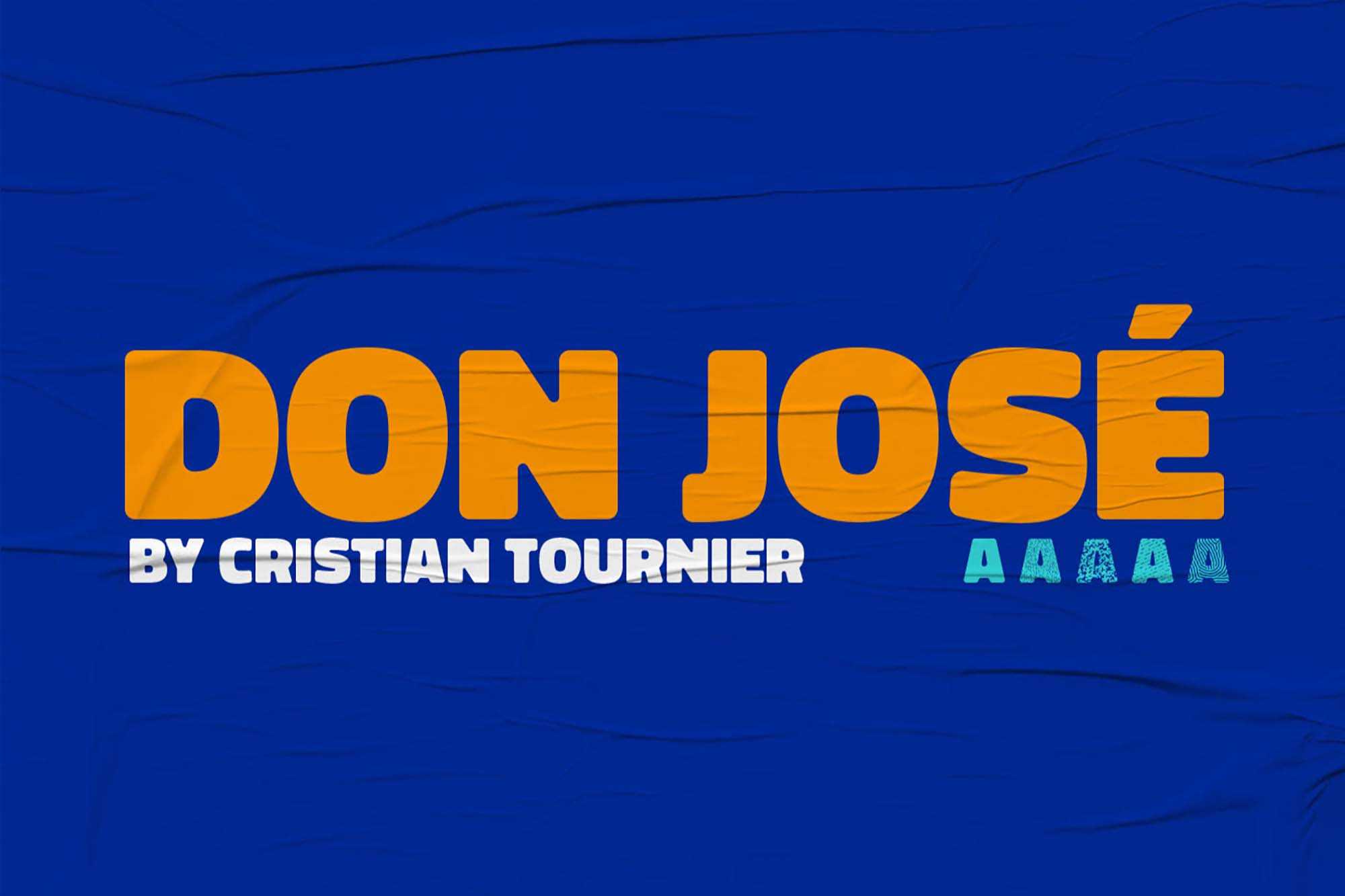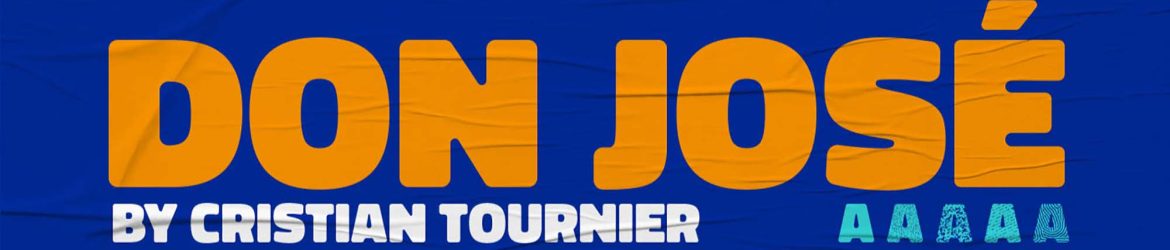
Don Jose Sans Serif Font – Download Grátis
Ajudando a criar design gráfico incrível, o font sans serif Don Jose é uma escolha ótima para projetos pessoais e comerciais. Ele foi desenvolvido por Cristian Tournier e oferece um design singular e versátil para os usuários. Se sua intenção é criar algo chamativo, com variedade e uma aparência autêntica, Don Jose é um recurso gráfico que merece ser testado. Se você está procurando por uma alternativa àgradável e moderna para suas criações visuais, este font pode ser perfeito. Além disso, sua natureza sem serif permite que sua tipografia se destaque, criando um impacto visual forte e limpo. Seja para cartazes, identidades, ou qualquer outro projeto gráfico, Don Jose é uma escolha sólida.